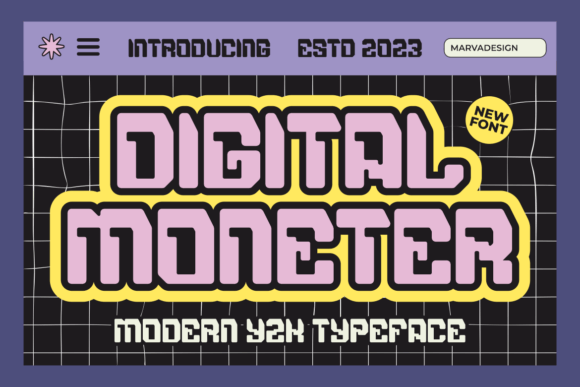
Digital Moneter
適切なデザイン要素を見つけるのは難しい場合がありますが、Digital Moneterは作品を即座に引き立てる優れたコレクションを提供します。
精密に作られたDigital Moneterは、クリーンなベクター、滑らかなタイポグラフィ、そして安心のための商用ライセンスを提供します。